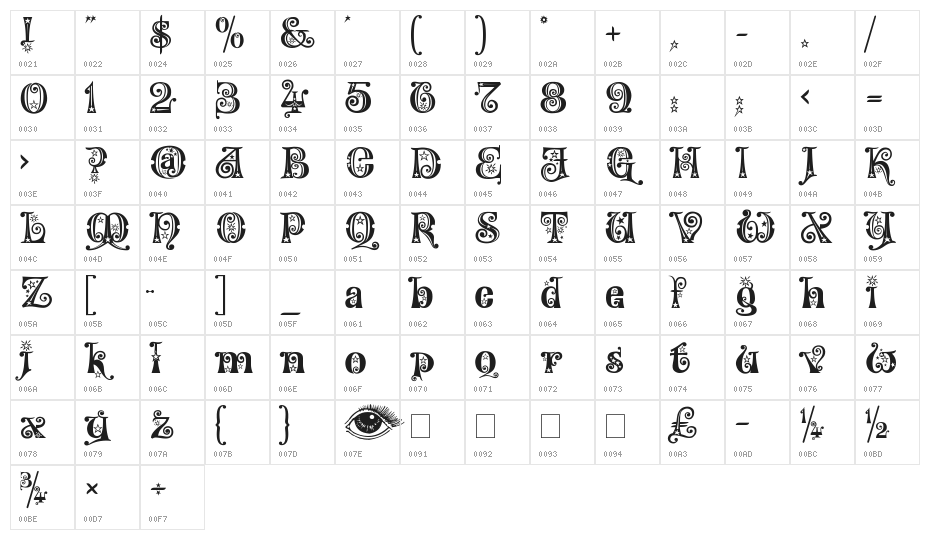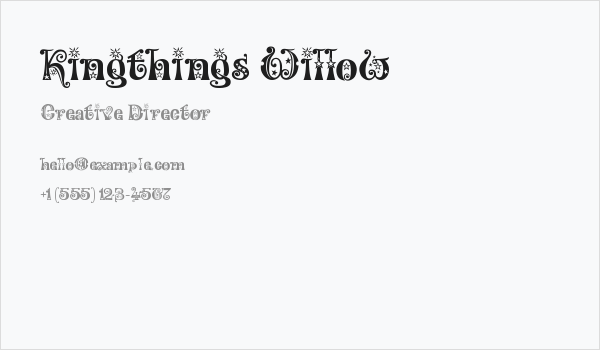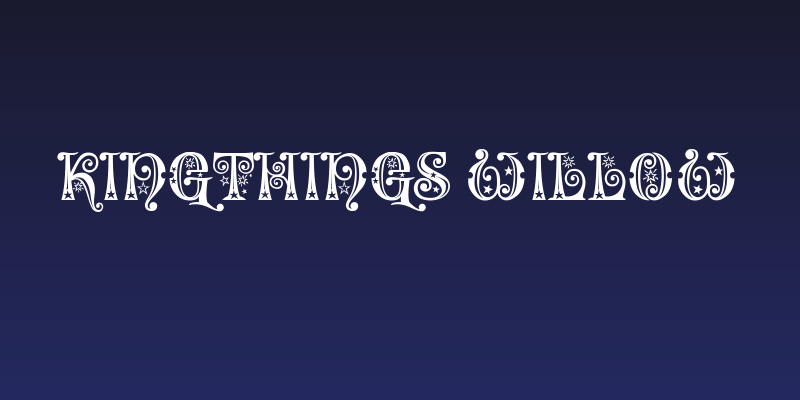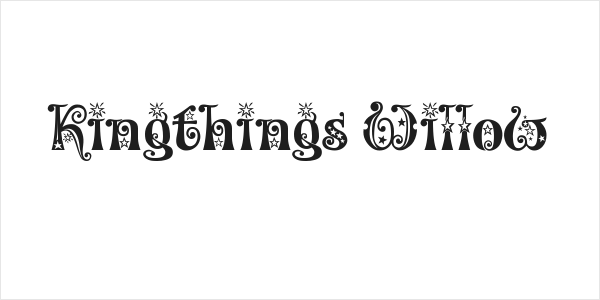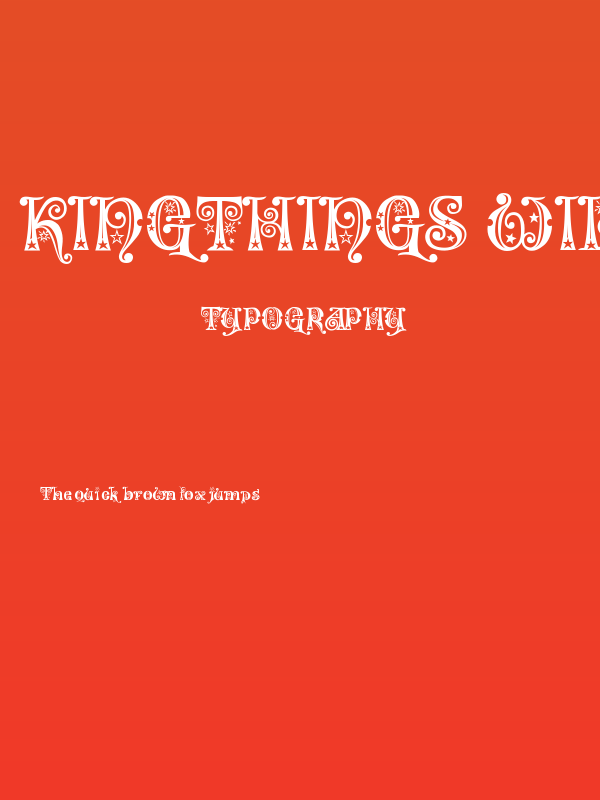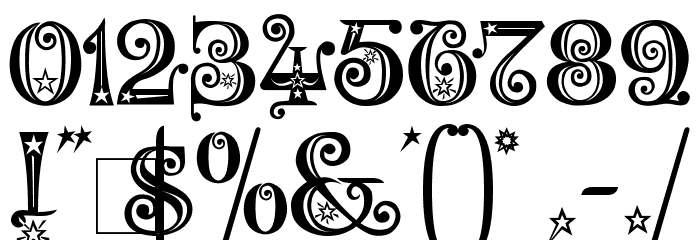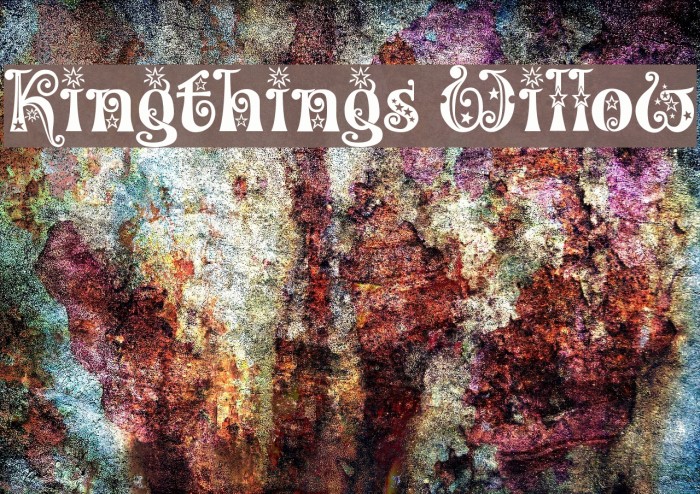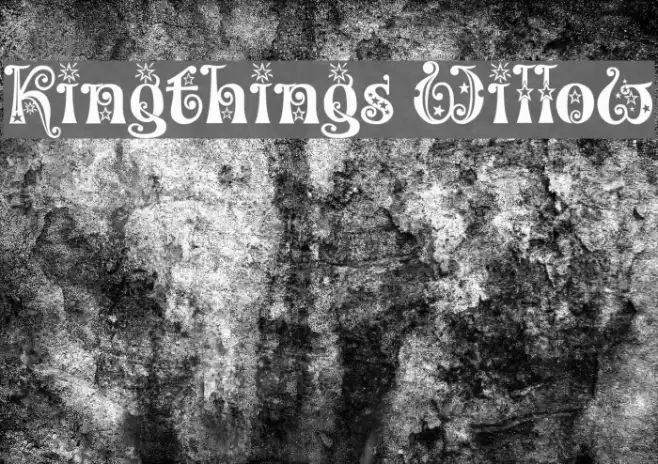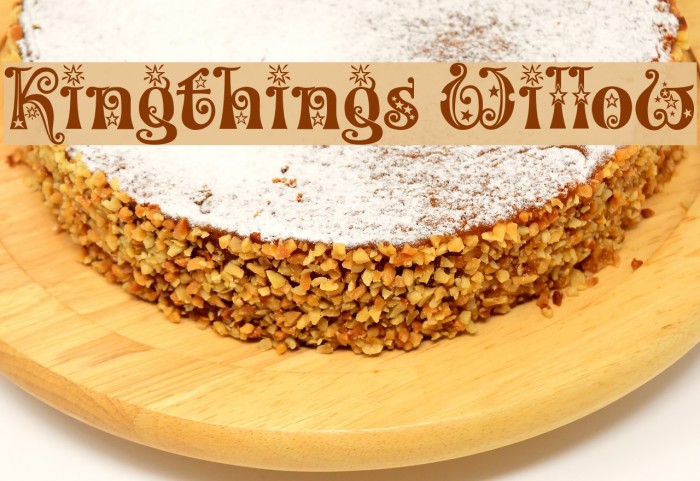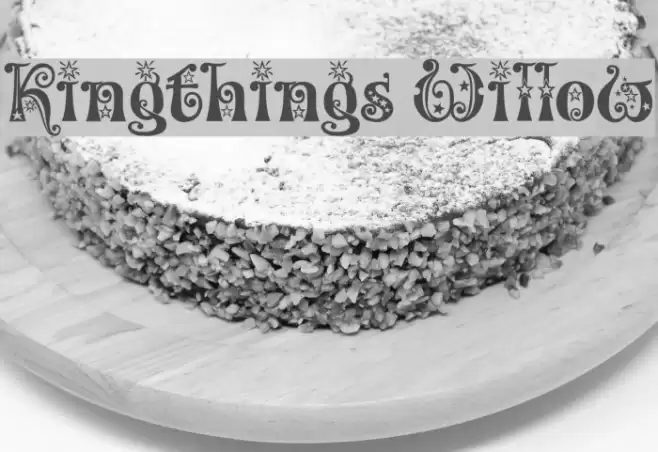
Kingthings Willow Font
| おすすめプロジェクト | Ideal for fantasy-themed invitations, children's book covers, magical event posters, and whimsical branding projects. |